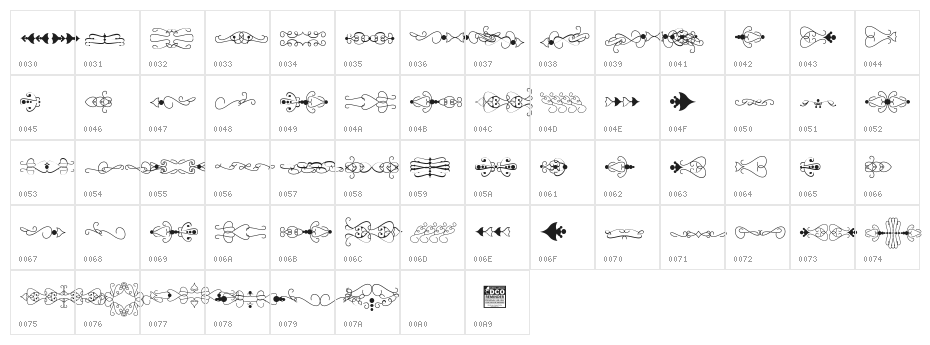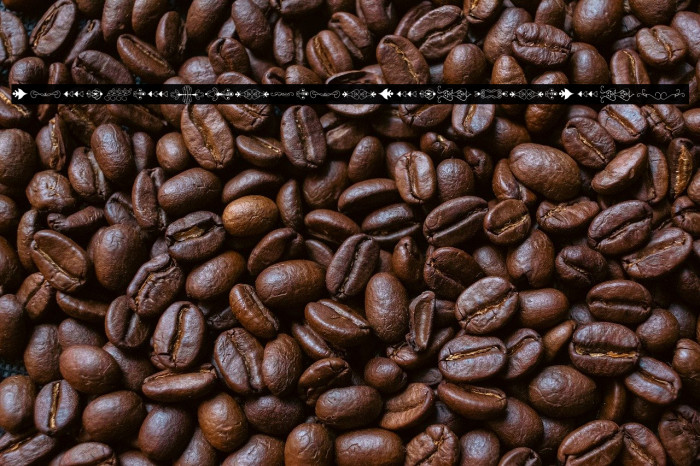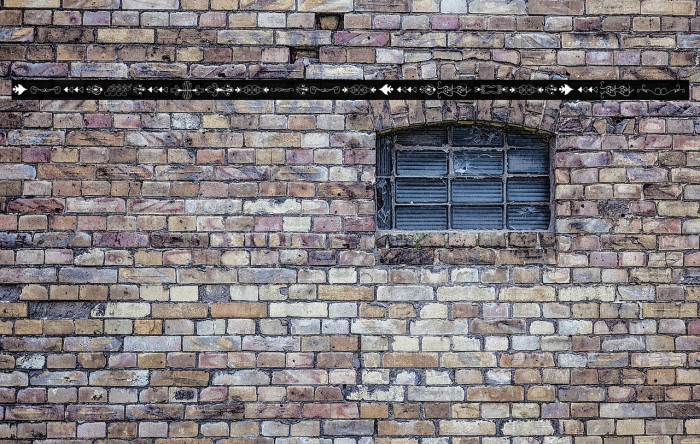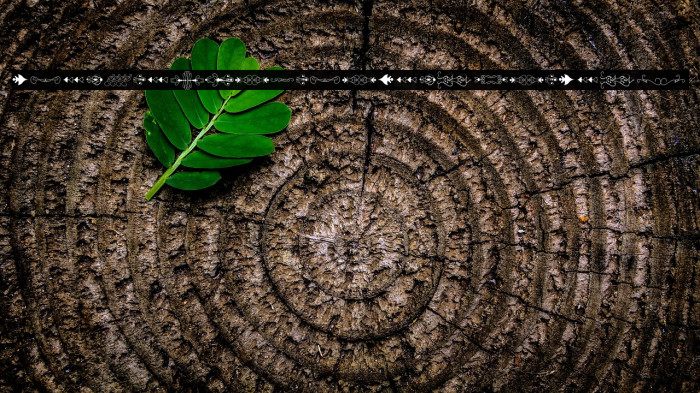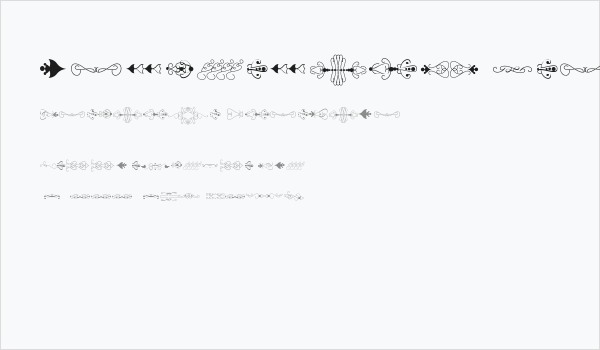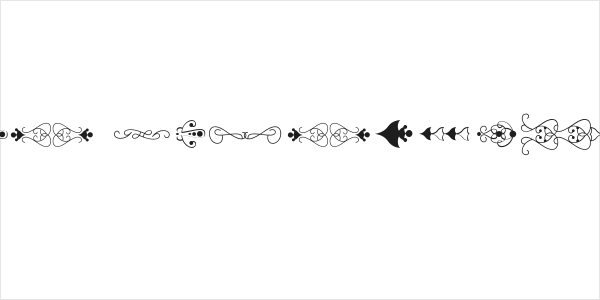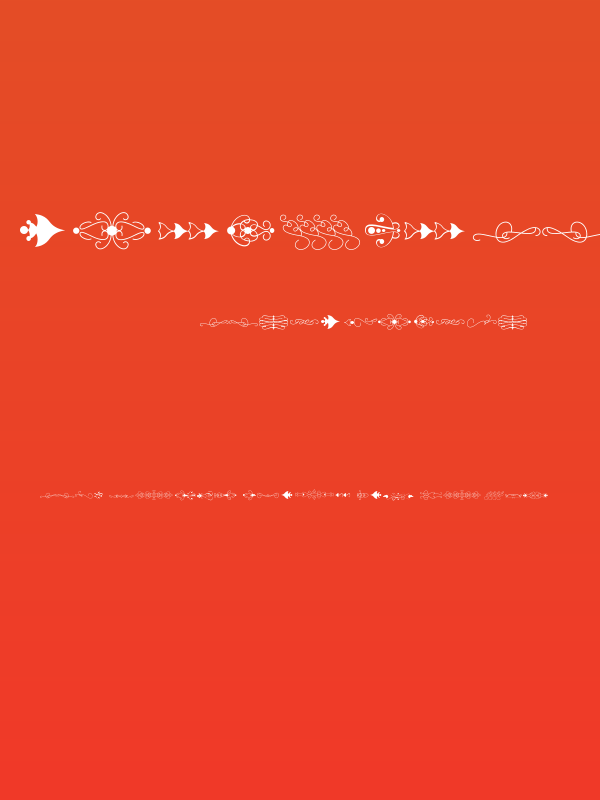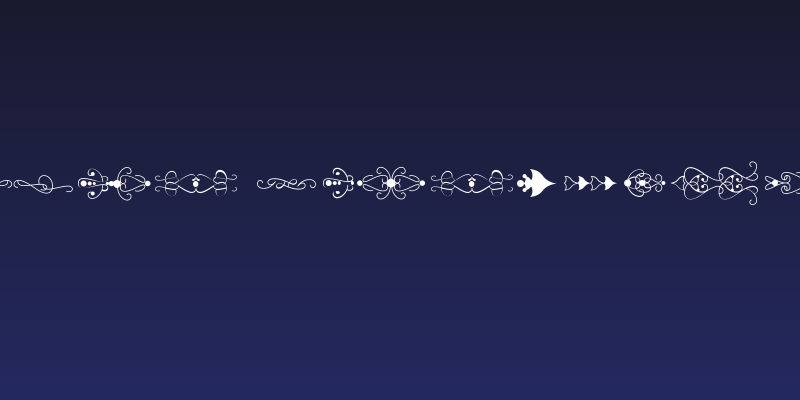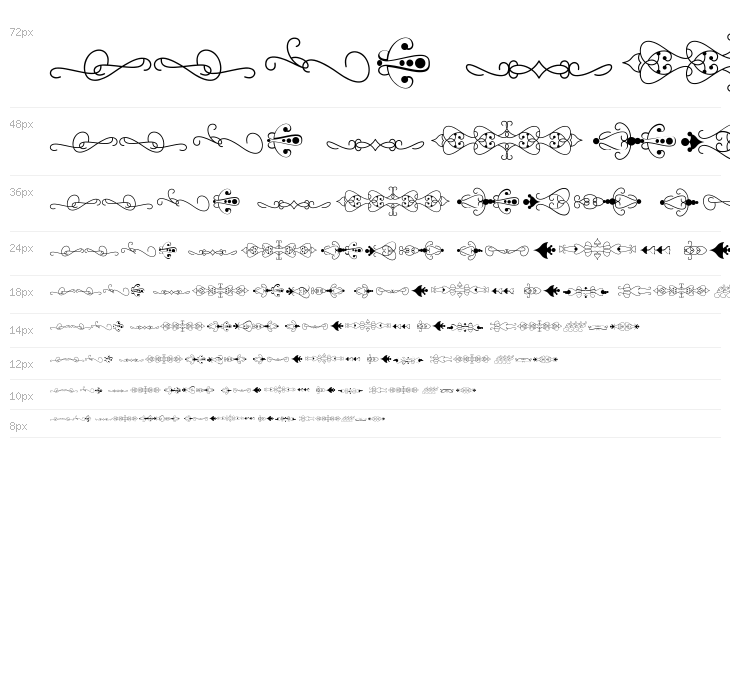
Ornamentis_PersonalUseOnly Font
| Anwendungsfall | Artistic embellishments, decorative borders, vintage designs. |
| Vorgeschlagene Projekte | Ideal for decorative borders, wedding invitations, artistic frames, and vintage-themed designs. |